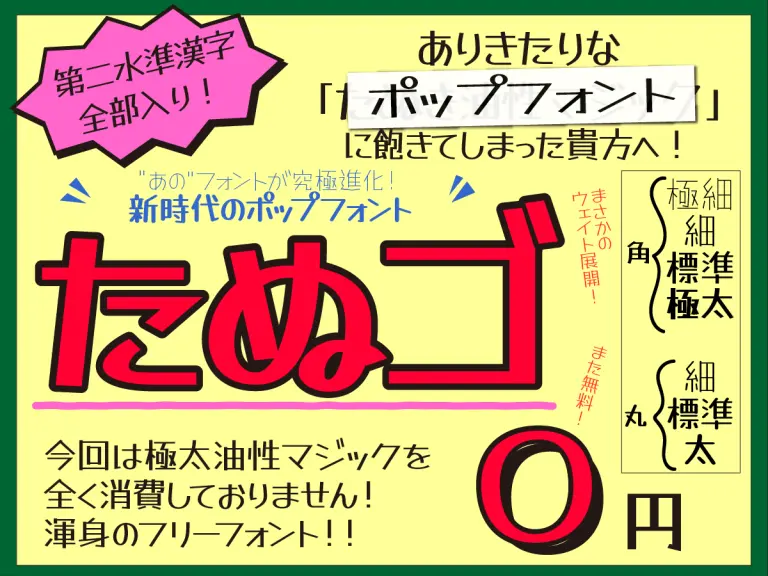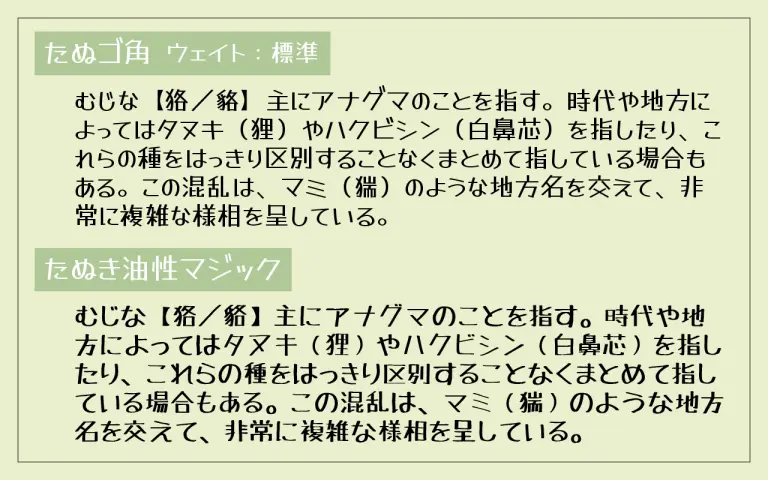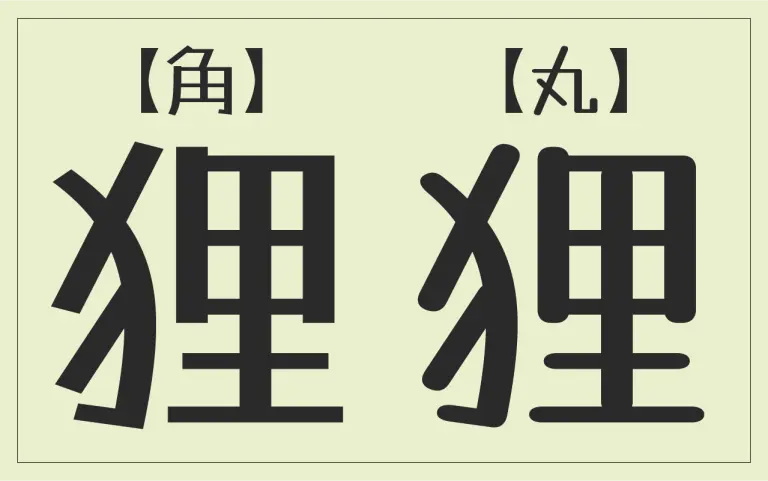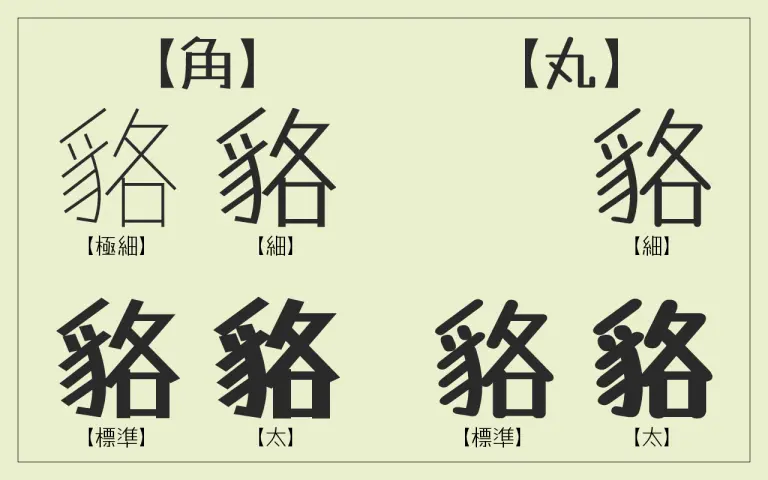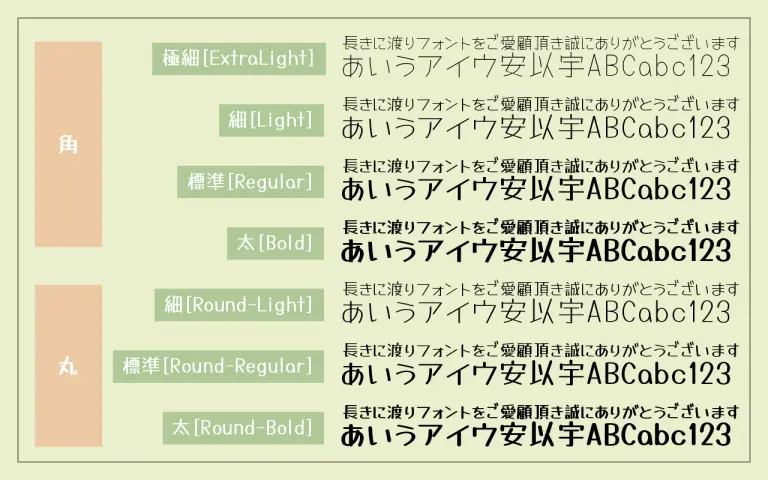
Tanugo(日文名:たぬゴ)是公開的自由字體『たぬき油性マジック』的更新版字體制作的字體,Tanugo手寫體保留了『たぬき油性マジック』的特徵,保持親切性的同時,更容易使用、容易閱讀,這是一款以可愛的類型設計為目標而製作的字體。
當サイトで公開しているフリーフォント『たぬき油性マジック』のリニューアル版フォントとして作成したフォントです。前作『たぬき油性マジック』の特徴である親しみやすさをキープしつつ、さらに使いやすく・読みやすく、かわいいタイプデザインを目指して作成したフォントです。
Tanugo有兩種樣式,字體名中帶“角”字的字體樣式,是硬邊的設計。而字體名中帶“丸”字的樣式,則邊角是圓頭的設計。
畫の端が角張ったデザインの『たぬゴ角』と、丸みを帯びたデザインの『たぬゴ丸』の2種類を用意しました。
另外,Tanugo手寫體【角】準備了超細、細、標準、太(ExtraLight·Light、Regular、Bold)的4個字重,Tanugo手寫體【丸】準備了細圓、標準丸、太丸(Light·Regular、Bold)3個字重。
また、『たぬゴ角』は極細・細・標準・太(ExtraLight・Light・Regular・Bold)の4ウェイト、『たぬゴ丸』は細丸・標準丸・太丸(Light・Regular・Bold)の3ウェイトを用意しています。